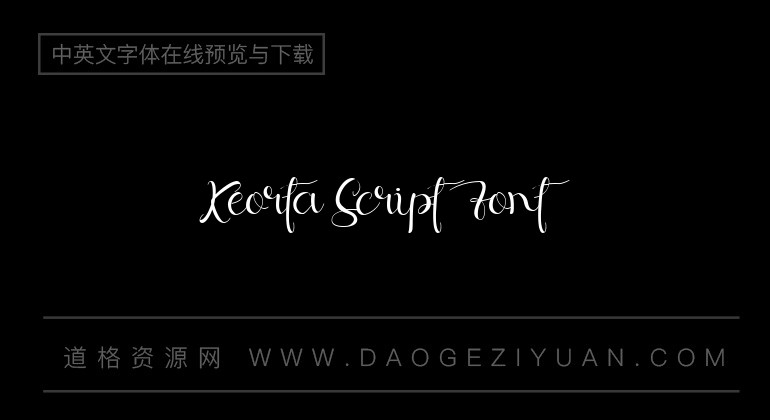
Keorta Script字体是一种美观且流畅的手写风格字体,具有独特的个性和美感。这种字体适用于各种不同的用途,如品牌标志、海报、广告、印刷品和网页设计等。 Keorta Script字体的特点是具有优美的曲线和线条,字母之间的间距均匀,风格自然流畅,给人一种优雅而又自然的感觉。此外,Keorta Script字体还包括许多特殊字符、符号和装饰性元素,使其更加有趣和多样化。 Keorta Script字体提供多种字体格式,包括OTF、TTF和WOFF等,适用于各种不同的操作系统和设计软件。内容介绍
Keorta Script Font是一款非常不错的手写艺术字体,具有很好的视觉感,适合于文化类的宣传设计、商业类品牌的广告和产品包装设计以及个性化文字排版等较多场景。